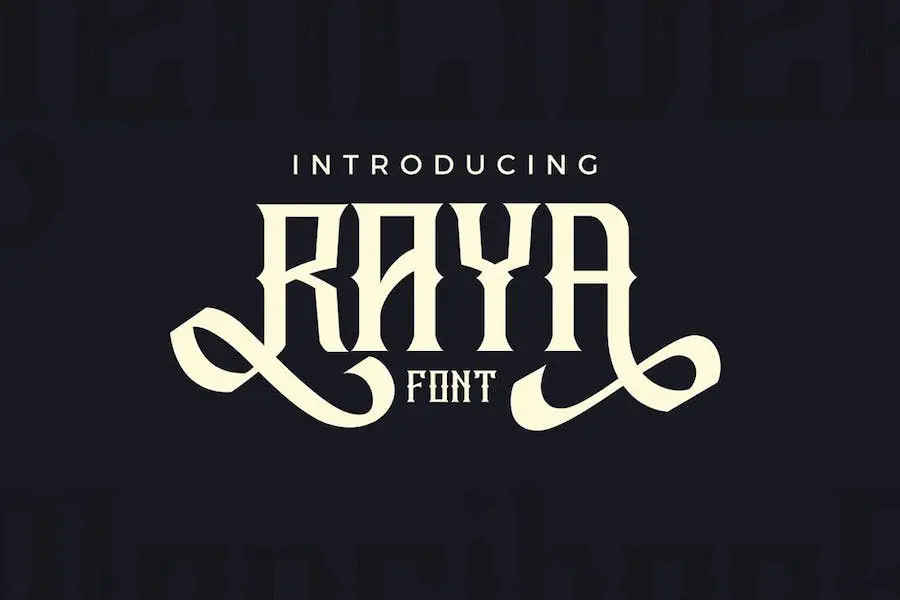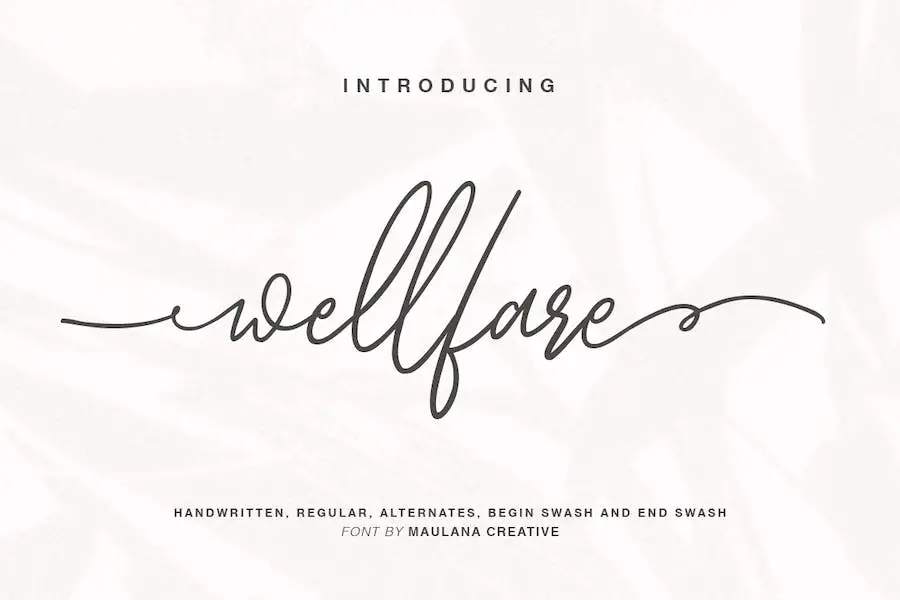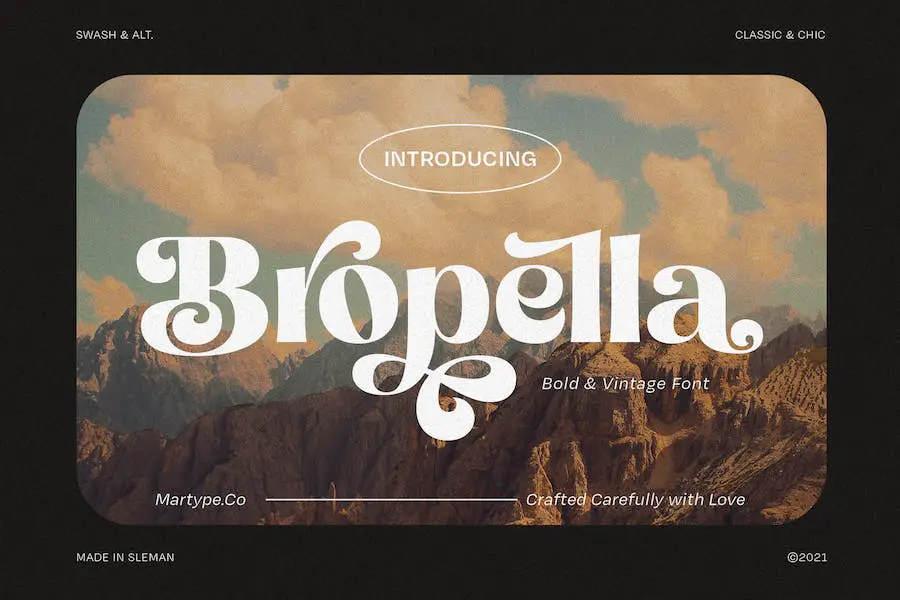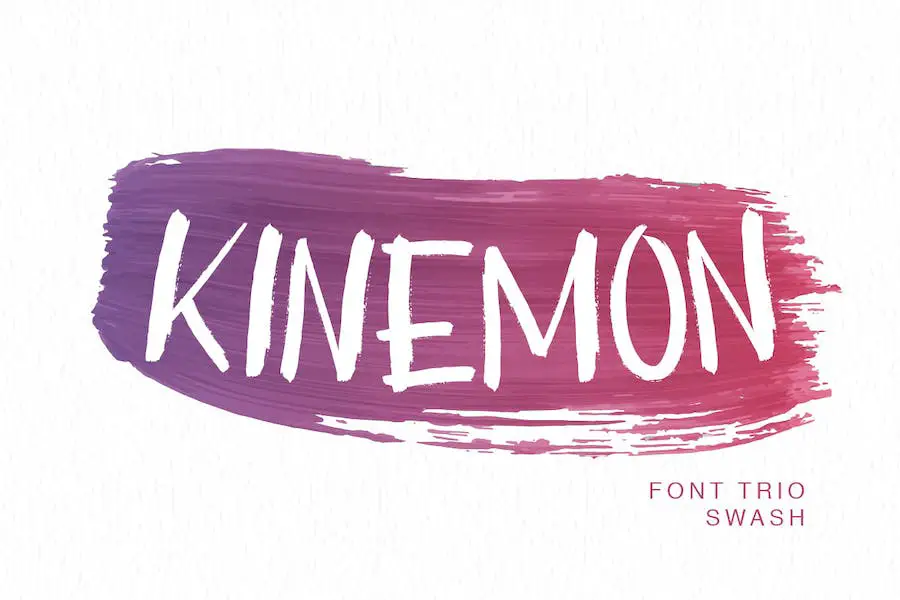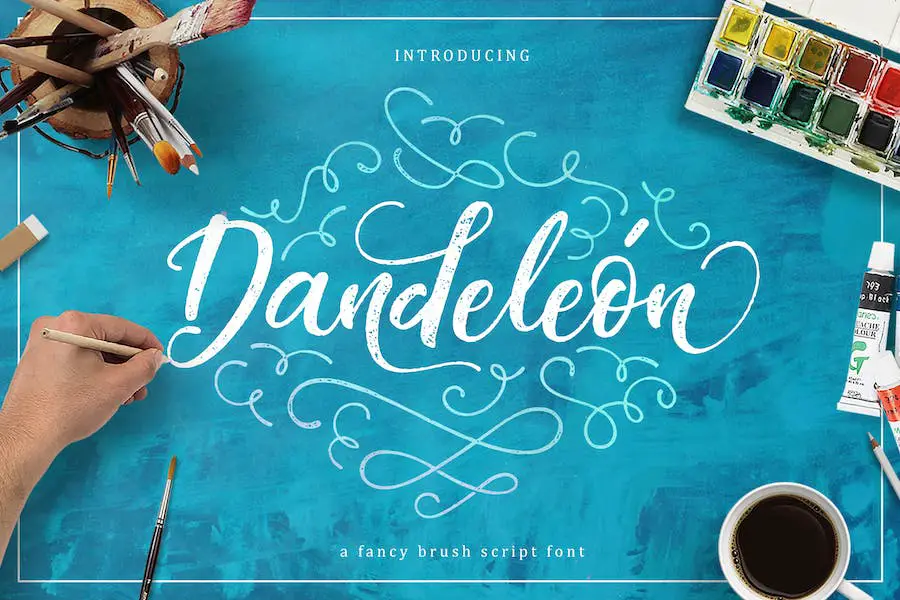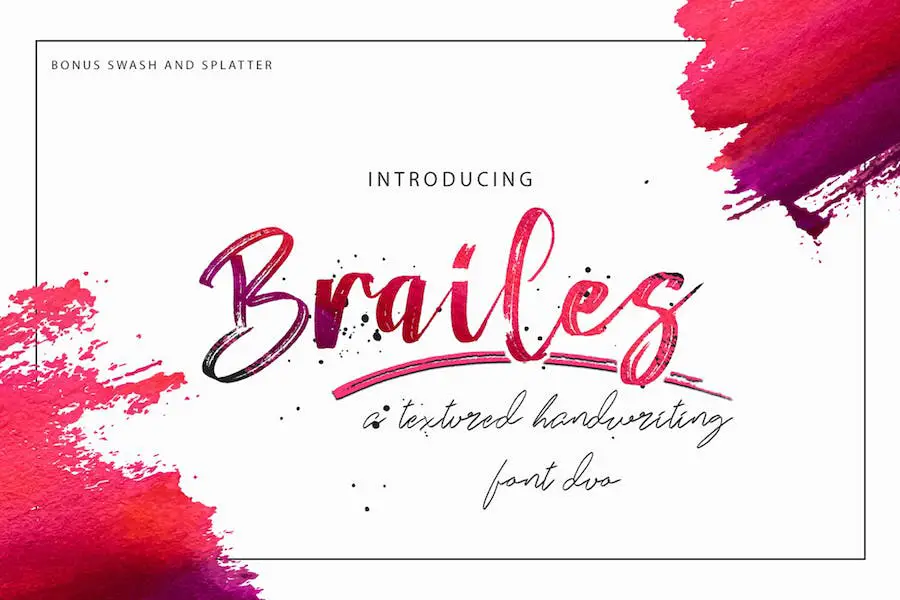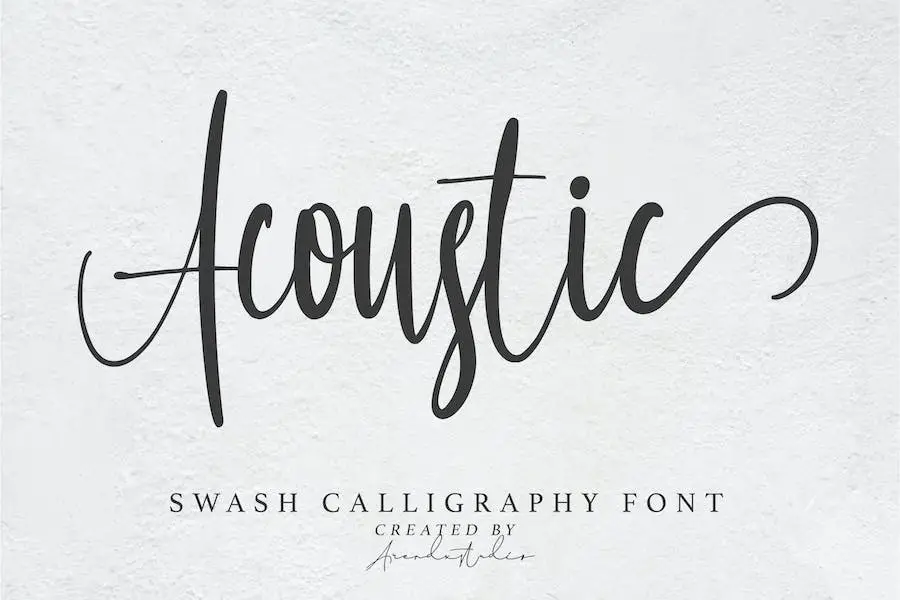
Immagina di avere un carattere che non solo sia bello ma aggiunga anche un tocco unico ai tuoi progetti. I caratteri Swash sono la soluzione perfetta per coloro che desiderano aggiungere un tocco di eleganza e raffinatezza ai propri progetti.
Questi caratteri presentano tratti eleganti e decorativi, spesso sotto forma di turbinii e svolazzi eleganti. Sono la scelta perfetta per qualsiasi cosa, dagli inviti di nozze ai loghi e ai materiali di branding.
In questo articolo presenteremo alcuni dei migliori caratteri swash attualmente disponibili sul mercato. Approfondiremo le caratteristiche di ciascun carattere, discuteremo la loro versatilità ed esploreremo esempi di come possono essere utilizzati efficacemente in diversi progetti di design.
Aligano
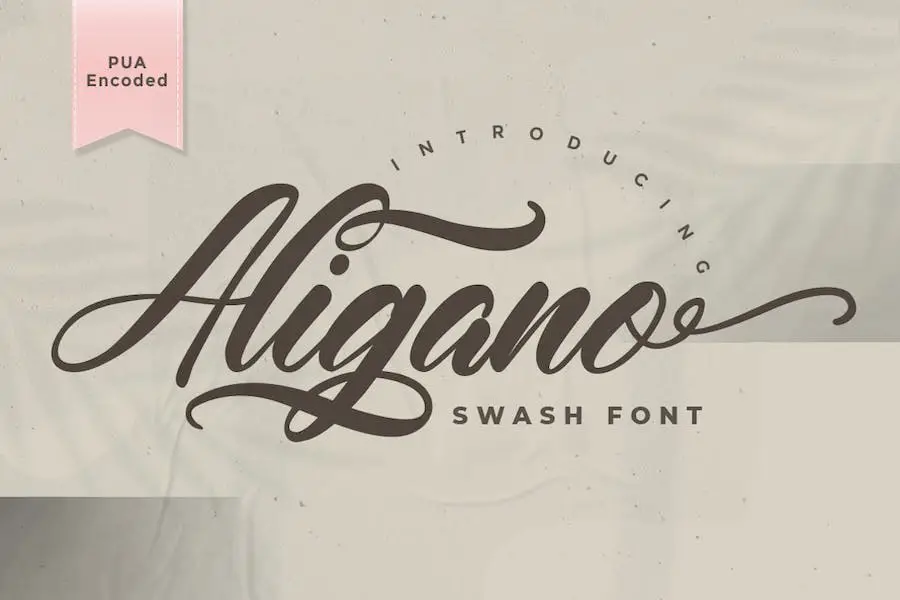
Aligano è uno straordinario carattere swash che eleverà i tuoi progetti di design al livello successivo. Questo squisito carattere scritto a mano è stato sapientemente realizzato per essere uno dei preferiti dai grafici.
I suoi dettagli intricati e artistici lo rendono una scelta straordinaria per qualsiasi progetto che richieda un tocco di eleganza e raffinatezza.
La bellezza di Aligano risiede nei suoi ornati unici. Questi tratti decorativi e decorazioni aggiungono un elemento affascinante e accattivante ai tuoi progetti.
Che tu stia creando inviti di nozze, loghi o grafica per social media, questo carattere migliorerà facilmente l'estetica generale e farà risaltare il tuo lavoro.
Uno dei grandi attributi di Aligano è la sua versatilità. È perfettamente adatto sia per i titoli che per il corpo del testo, garantendo che il tuo messaggio venga trasmesso con stile e chiarezza.
La fluidità e la grazia di questo carattere rendono piacevole lavorare con esso, fornendo un flusso continuo di parole che affascinano il lettore.
Immagina
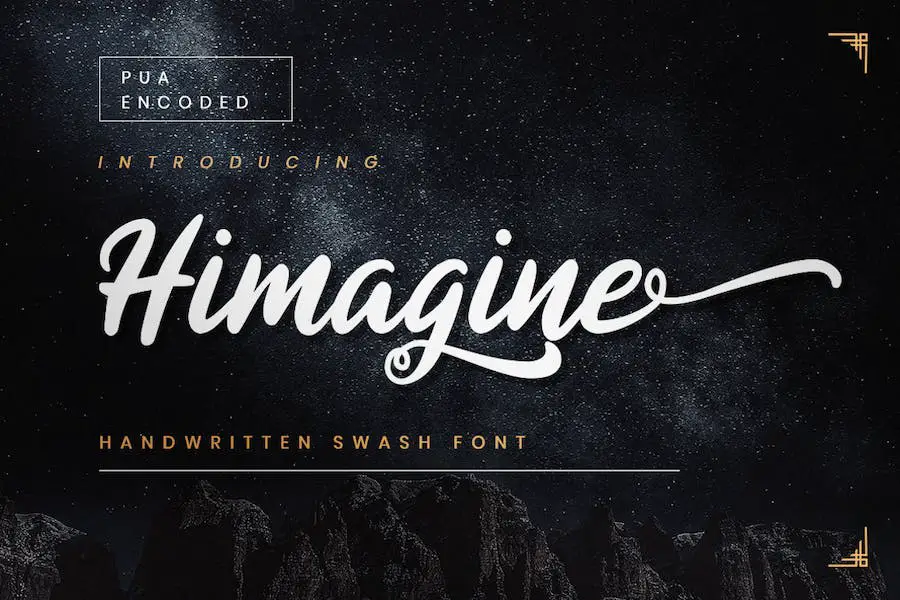
Himagine: uno straordinario carattere ornato che dona fascino e giocosità ai tuoi progetti di design. Questo carattere scritto a mano mostra deliziosi personaggi che sembrano ballare lungo la linea di base. Con i suoi ornati unici, aggiunge un tocco di eleganza e creatività a qualsiasi lavoro tipografico.
Il carattere Himagine è perfetto per i grafici che desiderano migliorare i propri progetti con un tocco di fantasia ed eleganza.
I suoi personaggi affascinanti e giocosi aggiungono un senso di divertimento e personalità a qualsiasi design, rendendolo versatile per varie applicazioni, come loghi, poster, inviti e altro ancora.
Ciò che distingue Himagine dagli altri caratteri ornati sono i suoi ornati meticolosamente realizzati che si estendono con grazia da ogni carattere. Questi ornati creano un flusso fluido e dinamico, aggiungendo movimento e interesse visivo alle tue composizioni tipografiche.
Sia che tu voglia creare titoli eleganti o aggiungere un elemento decorativo ai tuoi progetti, gli ornati di Himagine ti coprono.
Delberto
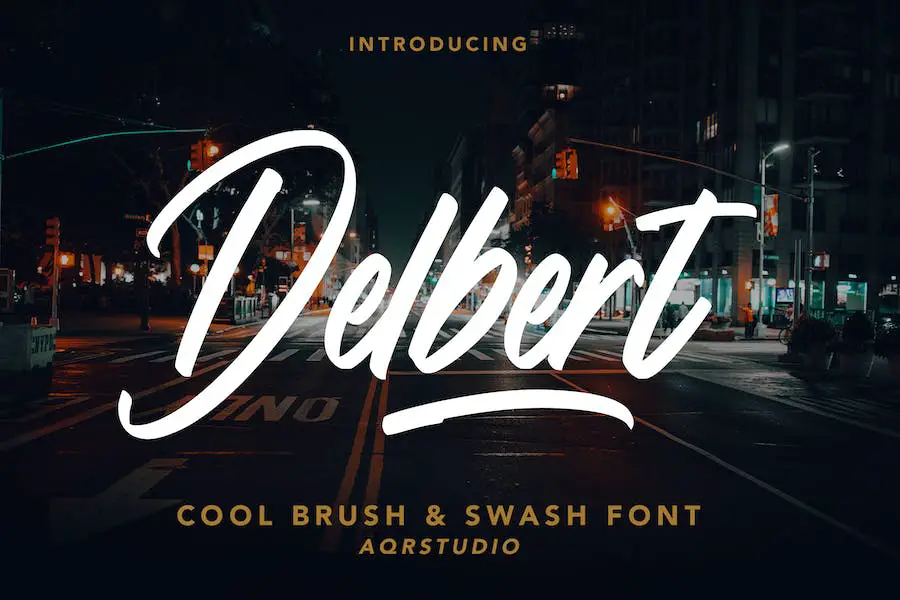
Delbert – Brush & Swash Font è un carattere tipografico versatile che soddisfa le esigenze dei grafici che desiderano migliorare i loro progetti con una tipografia straordinaria.
Con i suoi caratteri minuscoli, maiuscoli e simbolici, questo font offre un'ampia gamma di possibilità di espressione creativa. Inoltre, è compatibile con più lingue, il che lo rende la scelta ideale per progetti internazionali.
La versatilità di Delbert traspare dal suo design ispirato al pennello, aggiungendo un tocco artistico e artigianale a qualsiasi design. Che tu stia lavorando su un logo, un poster o un sito Web, questo carattere apporta un elemento unico e accattivante al tuo lavoro.
I suoi caratteri ornati, noti per i loro eleganti vortici e svolazzi, aggiungono un tocco di raffinatezza e fascino alla tua tipografia.
Una delle caratteristiche principali di Delbert è il supporto per l'uso multilingue. Ciò significa che, indipendentemente dalla lingua richiesta dal tuo progetto, questo carattere ti copre.